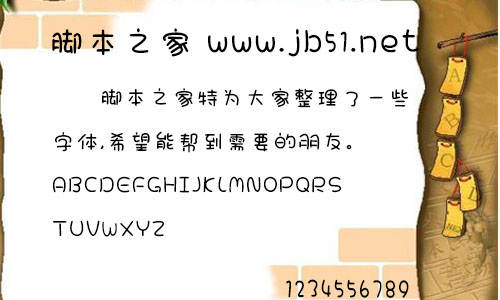
軟萌體是一款中文藝術(shù)字體,字如其名又軟又萌,字體筆觸清晰,字形結(jié)構(gòu)優(yōu)雅灑脫,整體看上去煞有靈動之感,適合應(yīng)用于藝術(shù)設(shè)計、平面宣傳設(shè)計、網(wǎng)頁設(shè)計,海報設(shè)計等領(lǐng)域,需要的朋友可以前來本站下載。